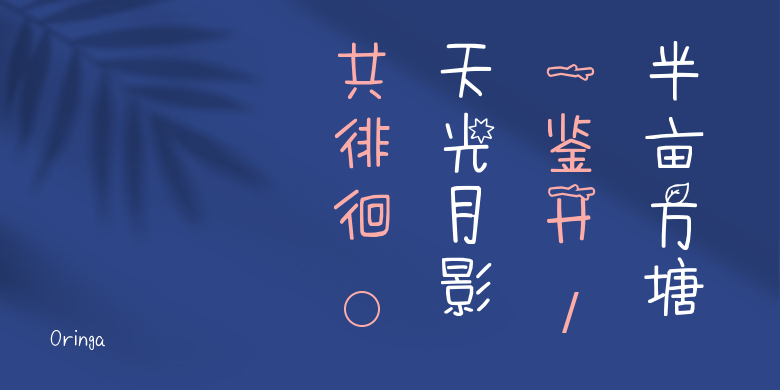
Oringa
Oringa,这款字体结构工整、笔画清晰,兼顾美观与易读性,适用于标题、正文、海报、包装、LOGO 等多种场景。字形优雅稳定,风格百搭耐看,适配日常排版与创意设计,让文字呈现更舒适、更具质感。Oringa一笔一画,皆是细节,以均衡的比例、流畅的线条打造舒适视觉体验,字形端正大气,风格简约现代。无论是商业设计、品牌宣传还是日常排版,都能轻松驾驭,让文字更有格调与力量。Oringa字体下载。